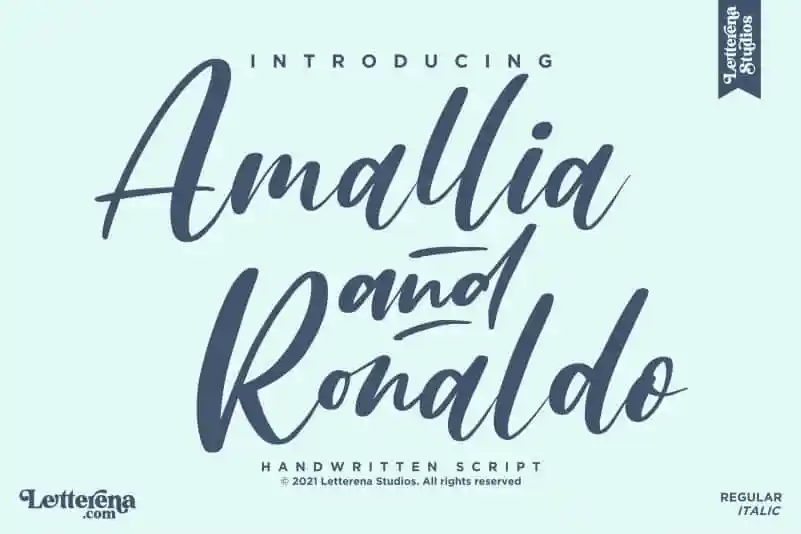
A ‘Amallia and Ronaldo Script Font’ do designer letterenastudios é uma elegante fonte de calligrafia ideal para os projetos mais sofisticados e detalhados, desde assinaturas até embalagens luxuosas. Seu estilo romântico cria um toque de exclusividade e requinte em qualquer projeto que você decida trazer à vida. Perfeita tanto para logos e marcas como para designs de prateleiras, embalagens de produtos, mugs personalizados ou até mesmo cartões de convite, essa fonte irá dar um toque único a seu trabalho. Seja para criar um estilo vintage, um design minimalista moderno ou algo que entre nesses tons delicados e artísticos, o ‘Amallia and Ronaldo Script Font’ é uma escolha inigualável. Esse recurso gráfico de alta qualidade não apenas tornará seus projetos mais atraentes, mas também os dará um toque especial. Não importa qual área você está trabalhando ou qual projeto está em sua mente – seja ele algo do dia-a-dia como uma embalagem para um produto simples ou algo grandioso e inovador, esta fonte de script é uma opção perfeita para deixar seu trabalho ainda mais impressionante.